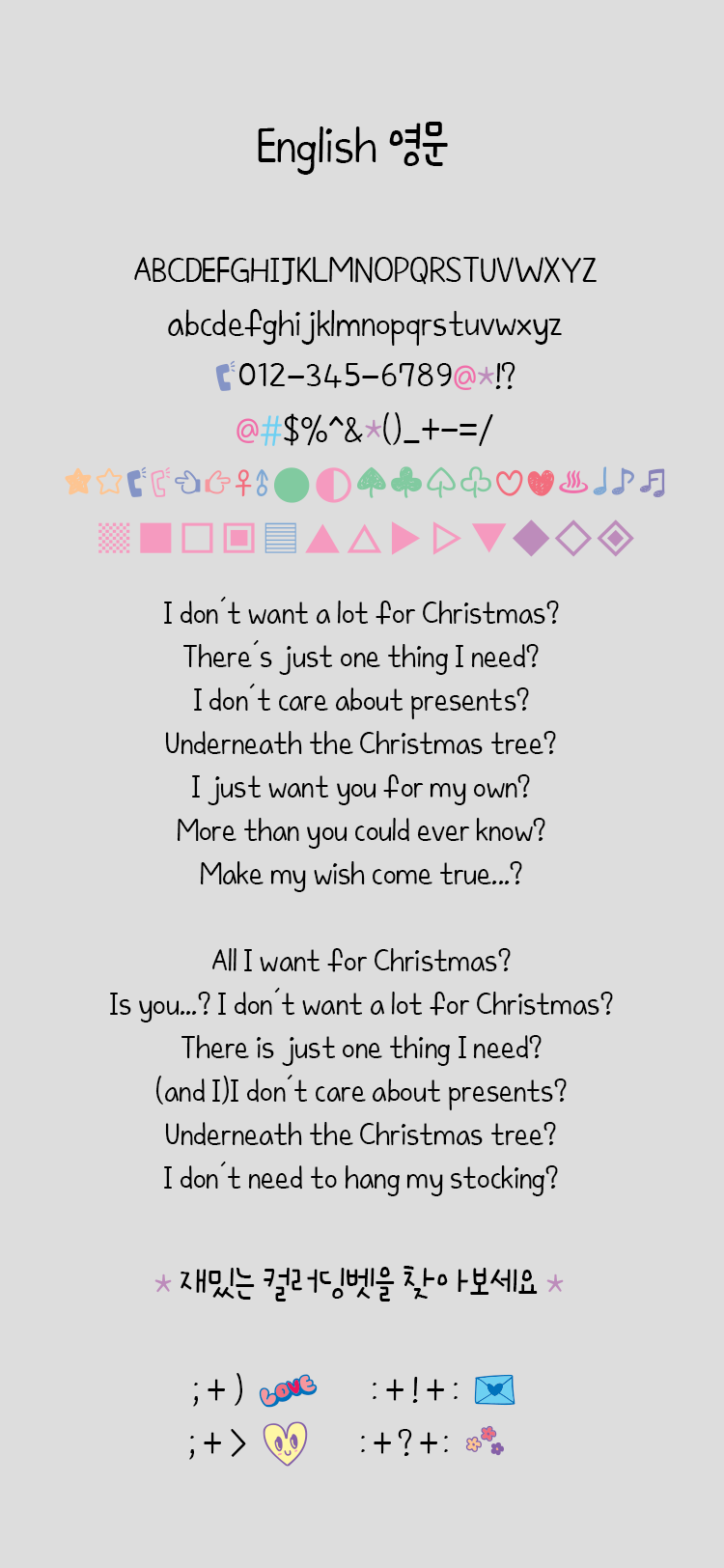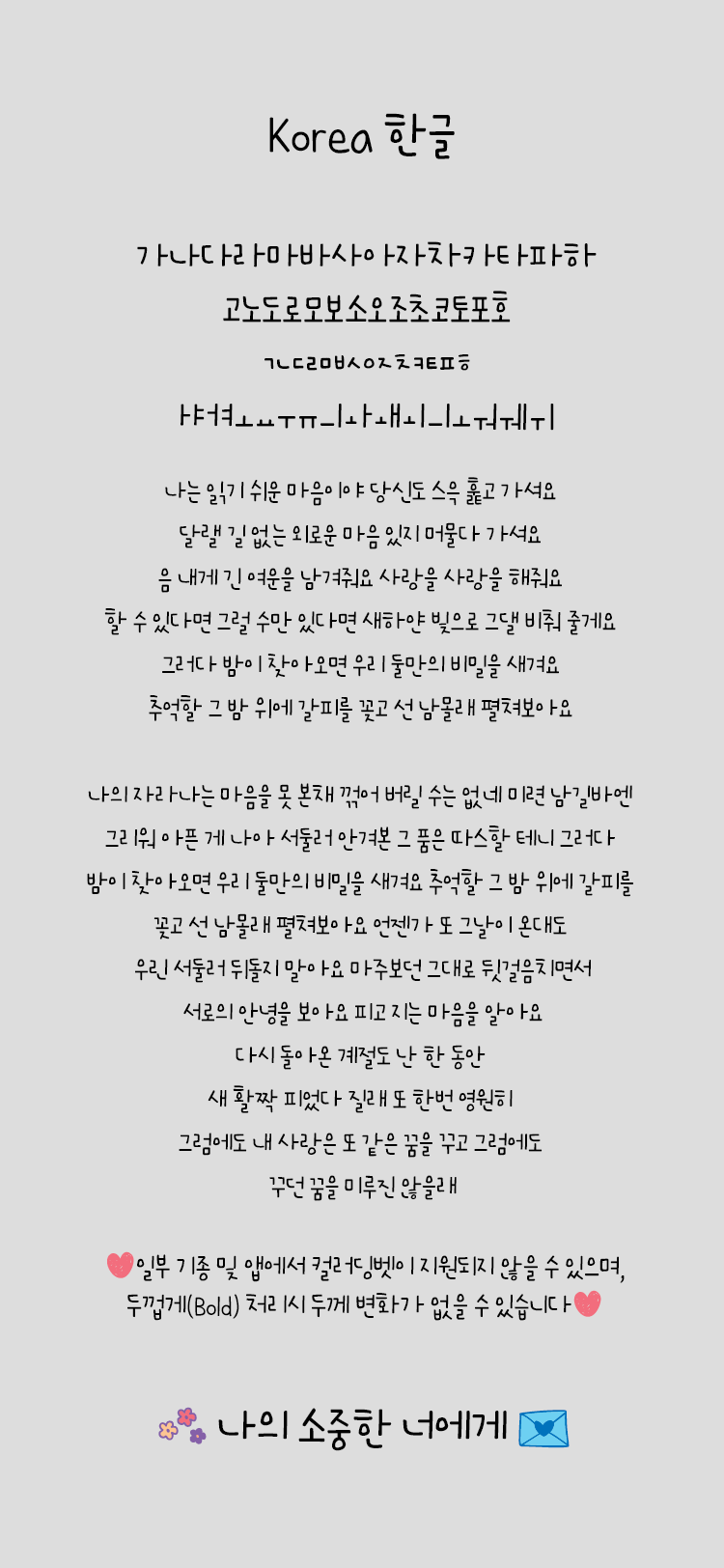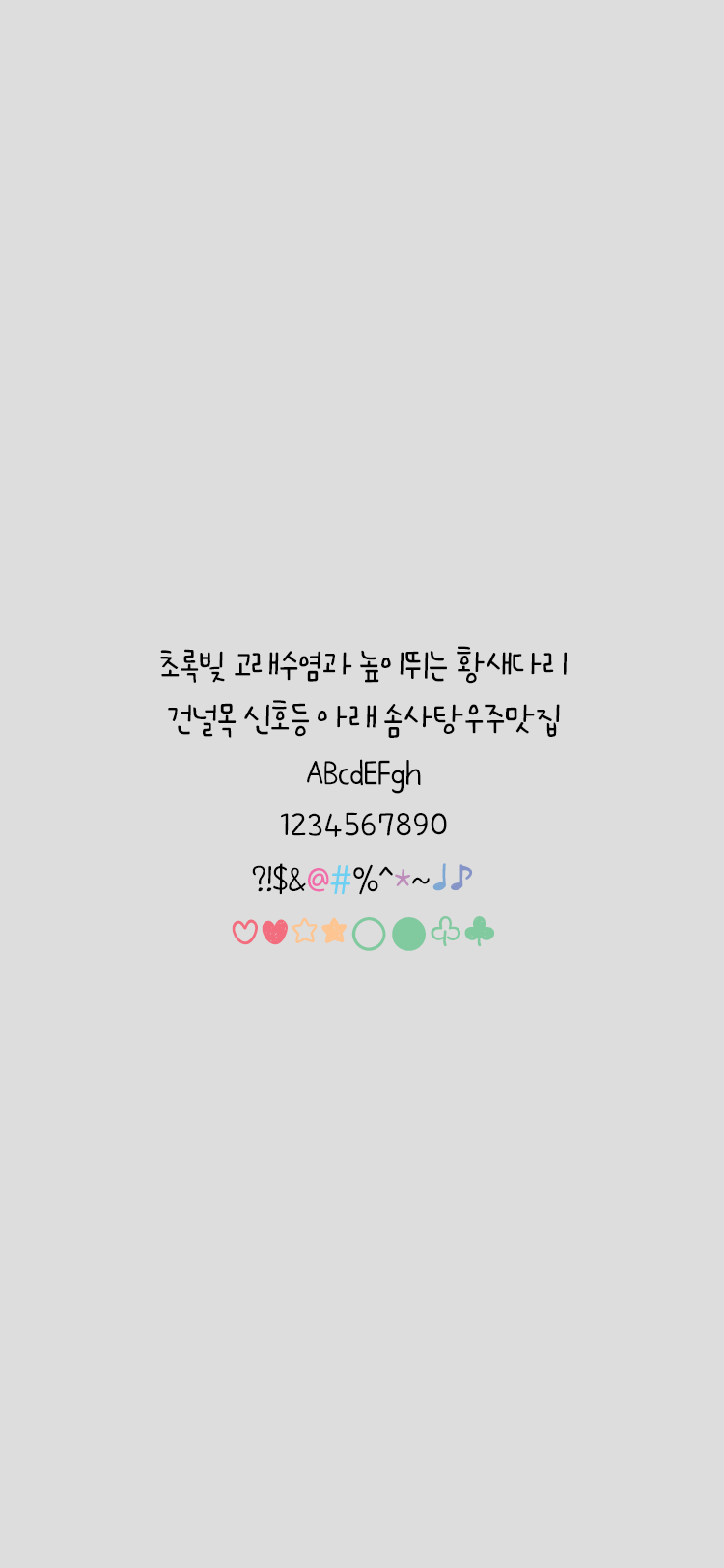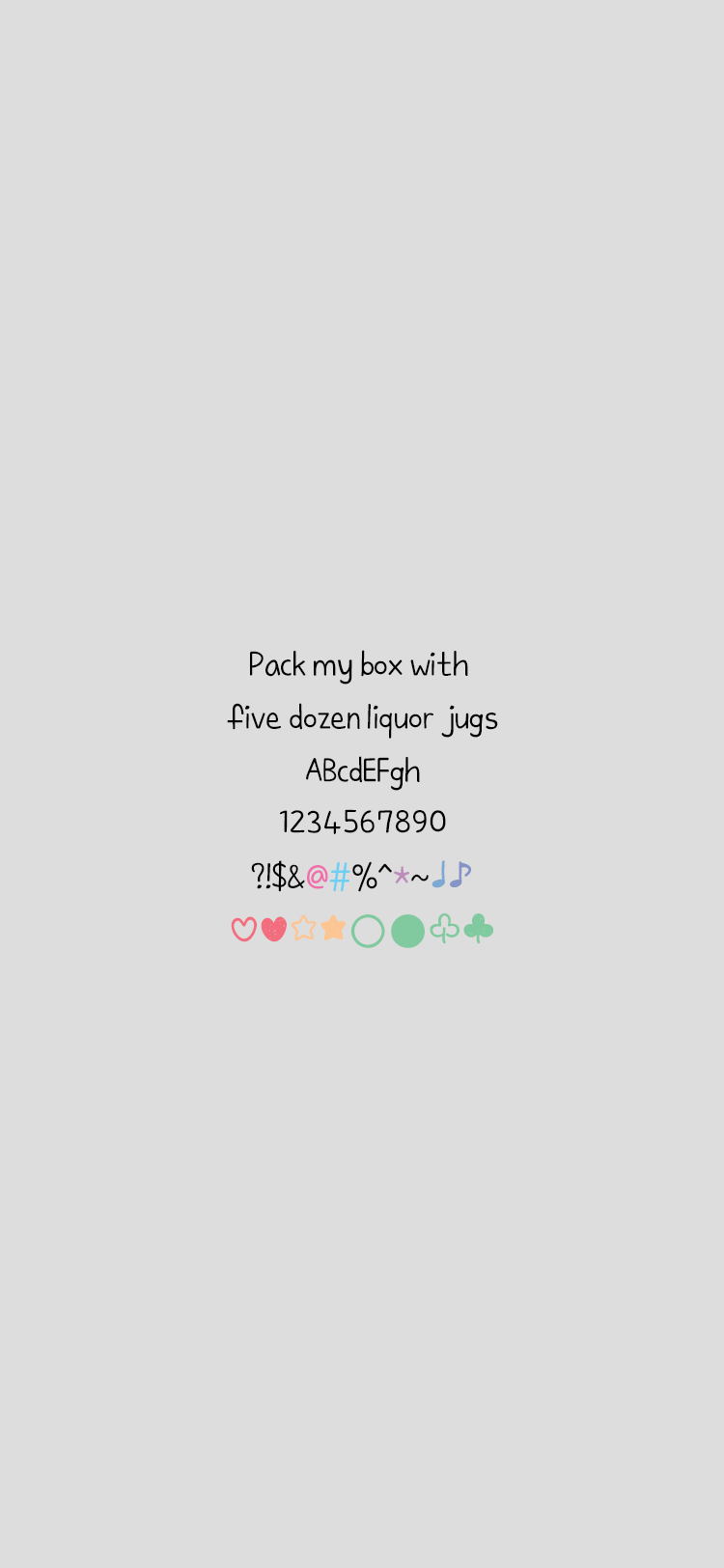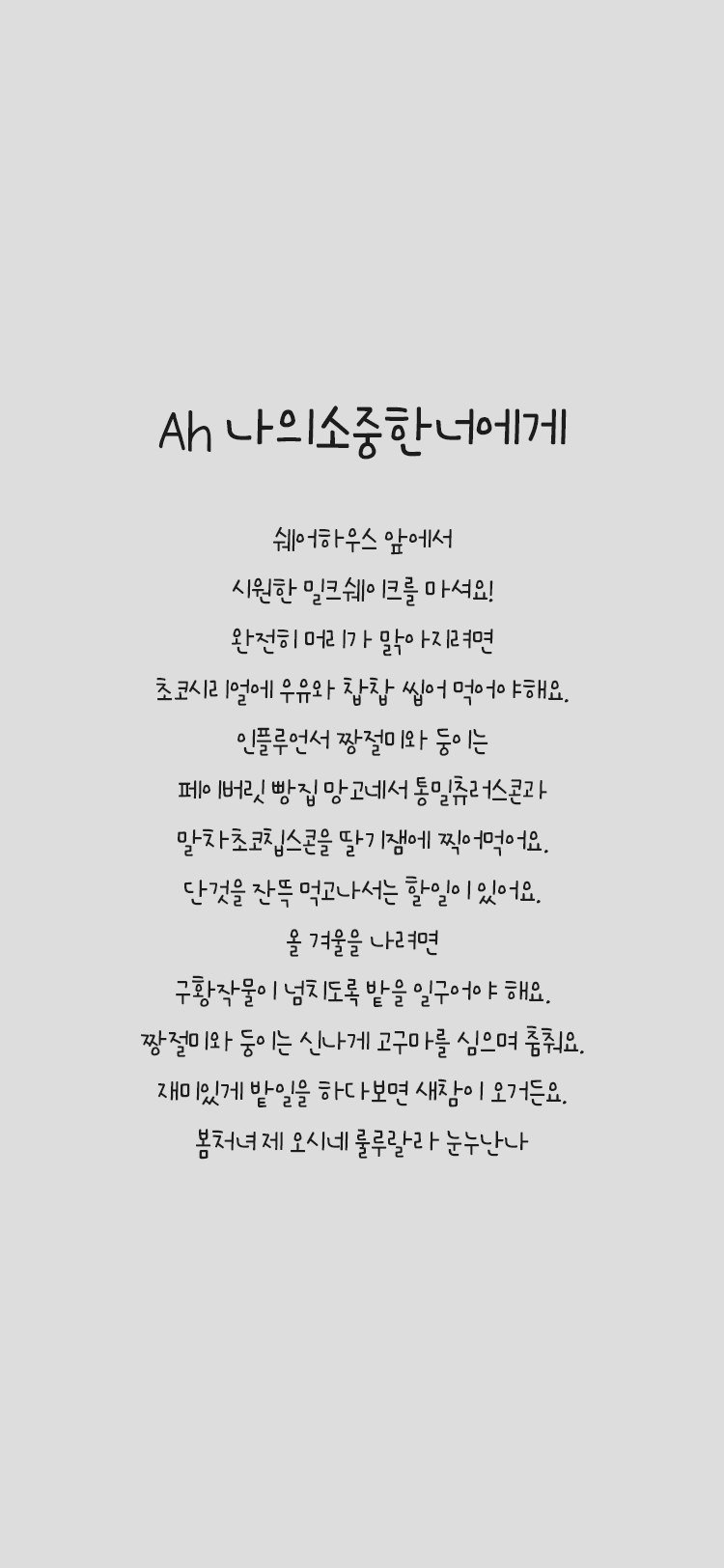
Ah 나의소중한너에게
이 서체는 자소들을 손으로 또박또박 쓴듯하면서도 자연스러운 형태가 특징입니다.
글줄은 중하단으로 시각적 흐름으로 설정하여 가독성 또한 장문으로 사용 시에도
무리 없도록 제작 하였습니다.
특별한 히든딩벳이 숨어져 있으니 찾아보시기 바랍니다. :>
• Ah 나의소중한너에게 / Ah Deartoyou